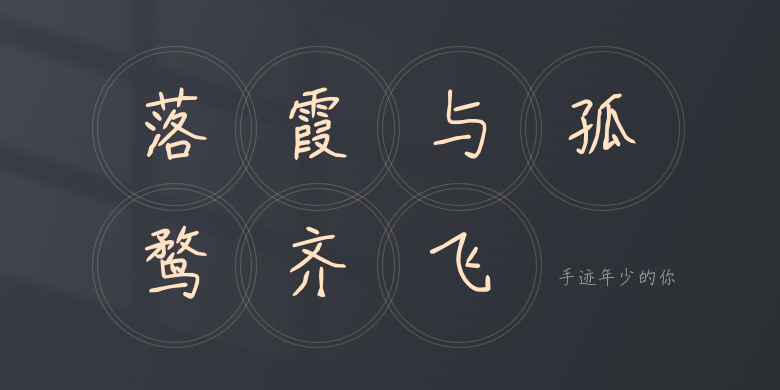
手迹年少的你
手迹年少的你,这款字体结构工整、笔画清晰,兼顾美观与易读性,适用于标题、正文、海报、包装、LOGO 等多种场景。字形优雅稳定,风格百搭耐看,适配日常排版与创意设计,让文字呈现更舒适、更具质感。手迹年少的你一笔一画,皆是细节,以均衡的比例、流畅的线条打造舒适视觉体验,字形端正大气,风格简约现代。无论是商业设计、品牌宣传还是日常排版,都能轻松驾驭,让文字更有格调与力量。手迹年少的你字体下载。